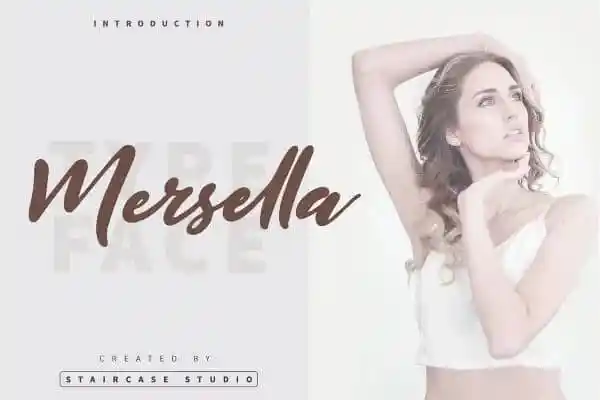
Mersella Script Font – Download Grátis
Descobrimos uma nova fonte chamada Mersella Script Font, que oferece ao designer um estilo elegante e natural dos traços da mão rápida. Ideal para promotores, esta font é perfeitamente adaptável para qualquer tipo de material – desde etiquetas de produto até logotipos fashion, capas de livros e materiais promocionais. Quem usa essa fonte experimentará uma sensação única de personalização real, já que a textura natural da escrita à mão está gravada na própria letra. Através de seu designer Staircase Studio, Mersella Script é perfeita para criar gráficos com um toque único e autêntico. Não importa o projeto – seja uma tag no Instagram ou até mesmo a capa do seu livro – essa fonte permite que você crie e personalize sua ideia de maneira autêntica, oferecendo ao designer uma ferramenta poderosa para explorar seus talentos criativos. Em suma, se está procurando por uma nova adição à sua coleção de fontes para trazer um toque único a qualquer projeto, Mersella Script é uma escolha inteligente. Seu design moderno e autêntico tornará seu trabalho ainda mais realista e inovador.